字体乃是PPT排版的基础性构成部分。字体选取恰当适宜的话,PPT便会呈现出专业之感。要是字体选取得不正确不对头的话,就算内容再怎么好,也将会显得十分的廉价。
存在这么一篇文章,是关于 PPT 字体进行推荐的,得讲讲究竟要如何去进行选择才不会出现错误。
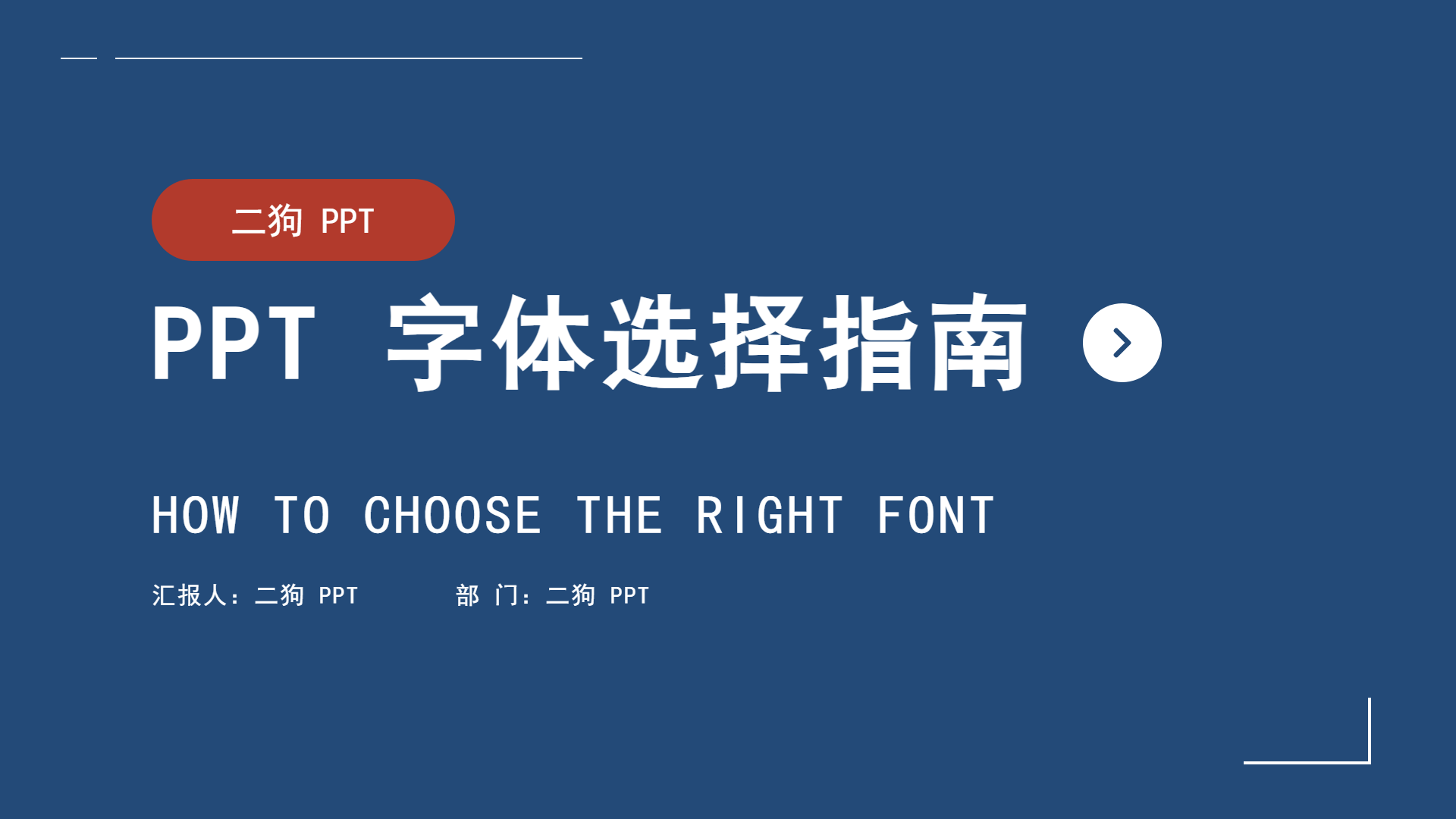
PPT 字体的选择原则
PPT字体的选取的重要准则,并非是好看,而是得清晰。
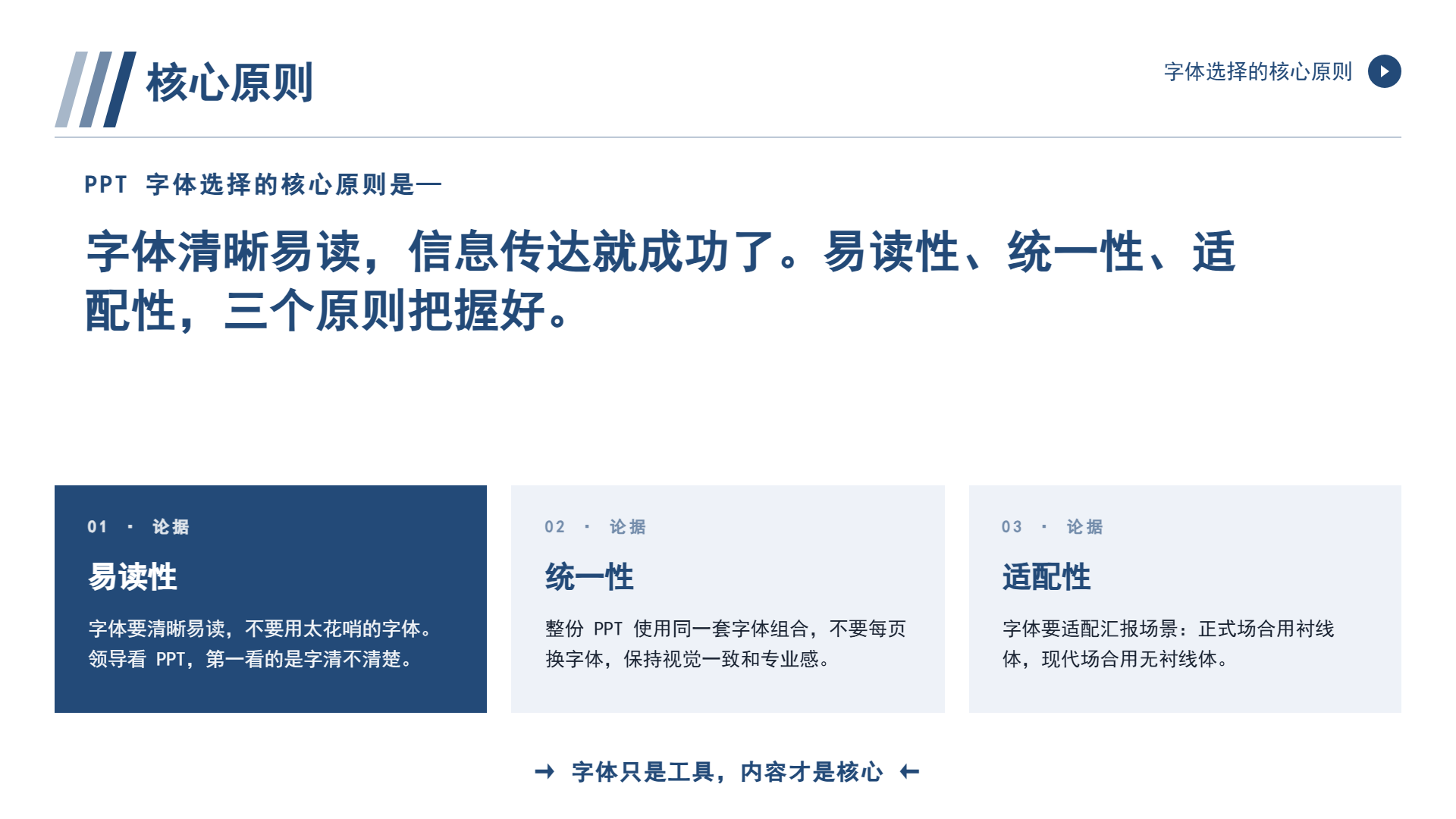
领导在查看PPT的时候,首要关注的是字是否清晰明了,而并非是字体好不好看。只要字体是清晰的,那么信息的传达就能够达成了。具体来说PPT字体的选择需要遵循三个方面的原则,分别是易读性、统一性以及适配性。
字体应当要清晰以便于阅读,不要采用过于花里胡哨的字体。整个 PPT 得使用同一种字体组合,不要每一页都更换字体。字体需要契合汇报的场景。在正式的场合运用衬线体,在现代的场合运用无衬线体。
PPT 字体的推荐组合
PPT字体予以推荐运用下面这些组合的状况。
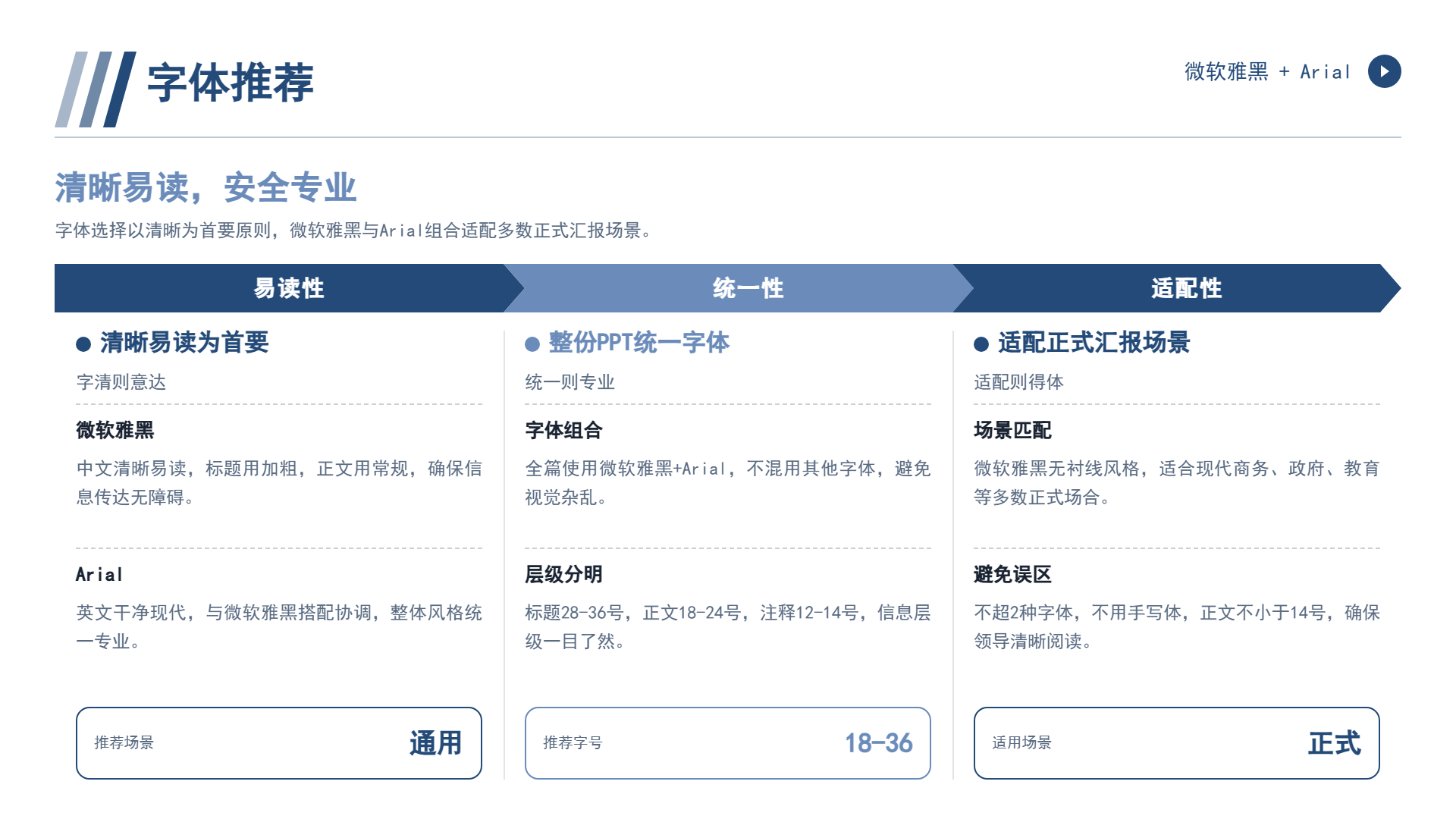
微软雅黑是一种较为安全的选择。微软雅黑看起来清晰还挺好读的,Arial,显得干净而且还挺现代的。标题使用加粗的微软雅黑,正文就用常规的微软雅黑,英文就用Arial。思源黑体是一种比较现代的选择。思源黑体的线条很清晰,Roboto简洁而且又现代。比较适合互联网和科技公司。宋体是最为正式的选择。宋体正式又稳重,Times New Roman经典而且又正式。适合国企还有学术汇报。
PPT 字体的字号建议
在 PowerPoint 字体的运用过程当中,字号的选取那可是一件至关重要的事情。
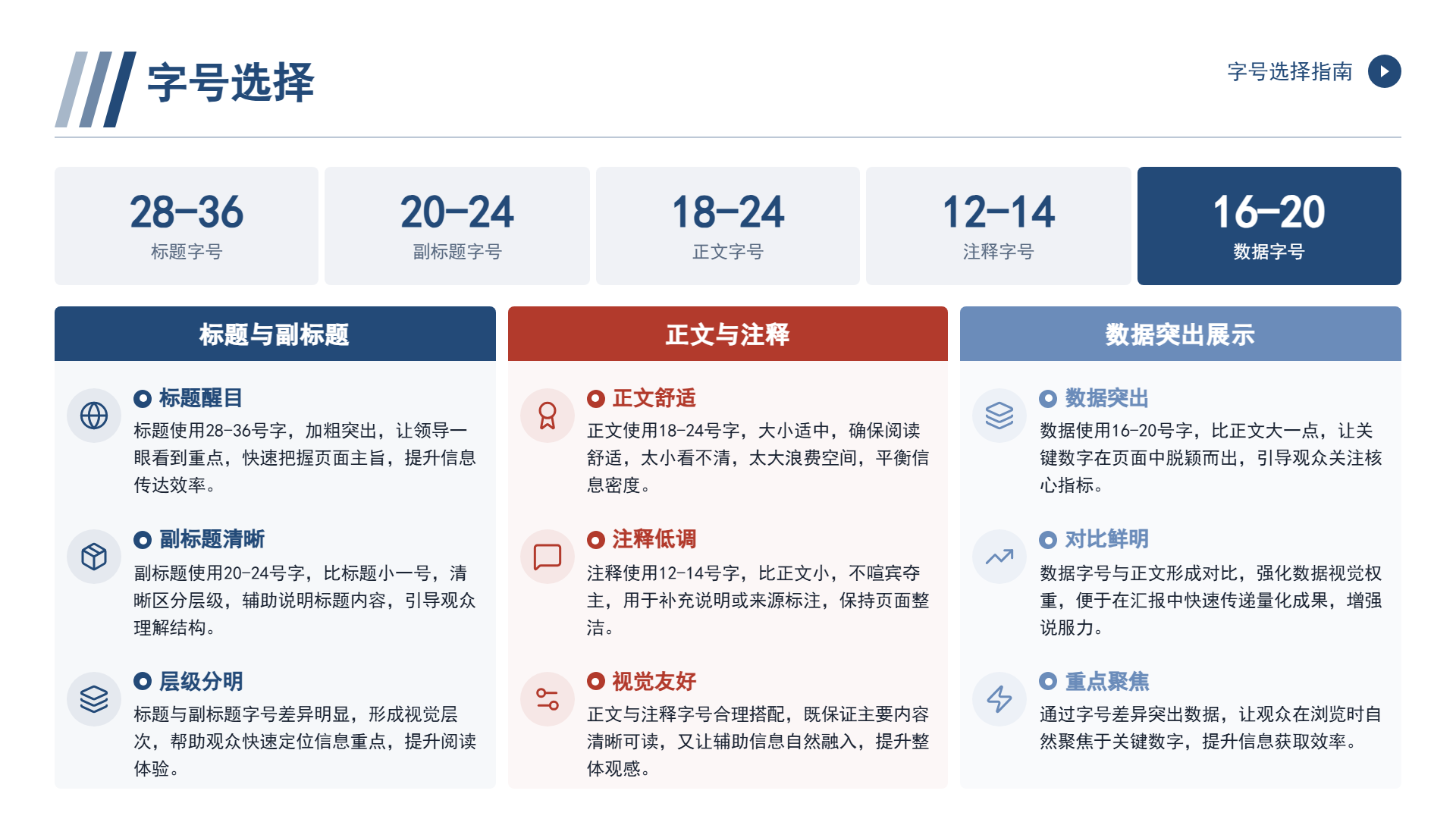
标题部分:运用28到36号字体,要让标题足够醒目,好让领导一眼就能看到。副标题部分:采用20到24号字体,要清晰明了,且比标题字体小一些。正文部分:使用18到24号字体,要让人看着感觉舒适,太小了会看不清,太大了又会造成空间的浪费。注释部分:运用12到14号字体,要小一点,不能去抢了主要内容的风头。数据部分:采用16到20号字体,要突出显示,比正文字体大那么一点。
PPT 字体的常见误区
PPT字体方面存在着好几个常见的错误性的认知,如果可以躲开这些错误之处,那么在字体的运用方面就已经成功了一大半。
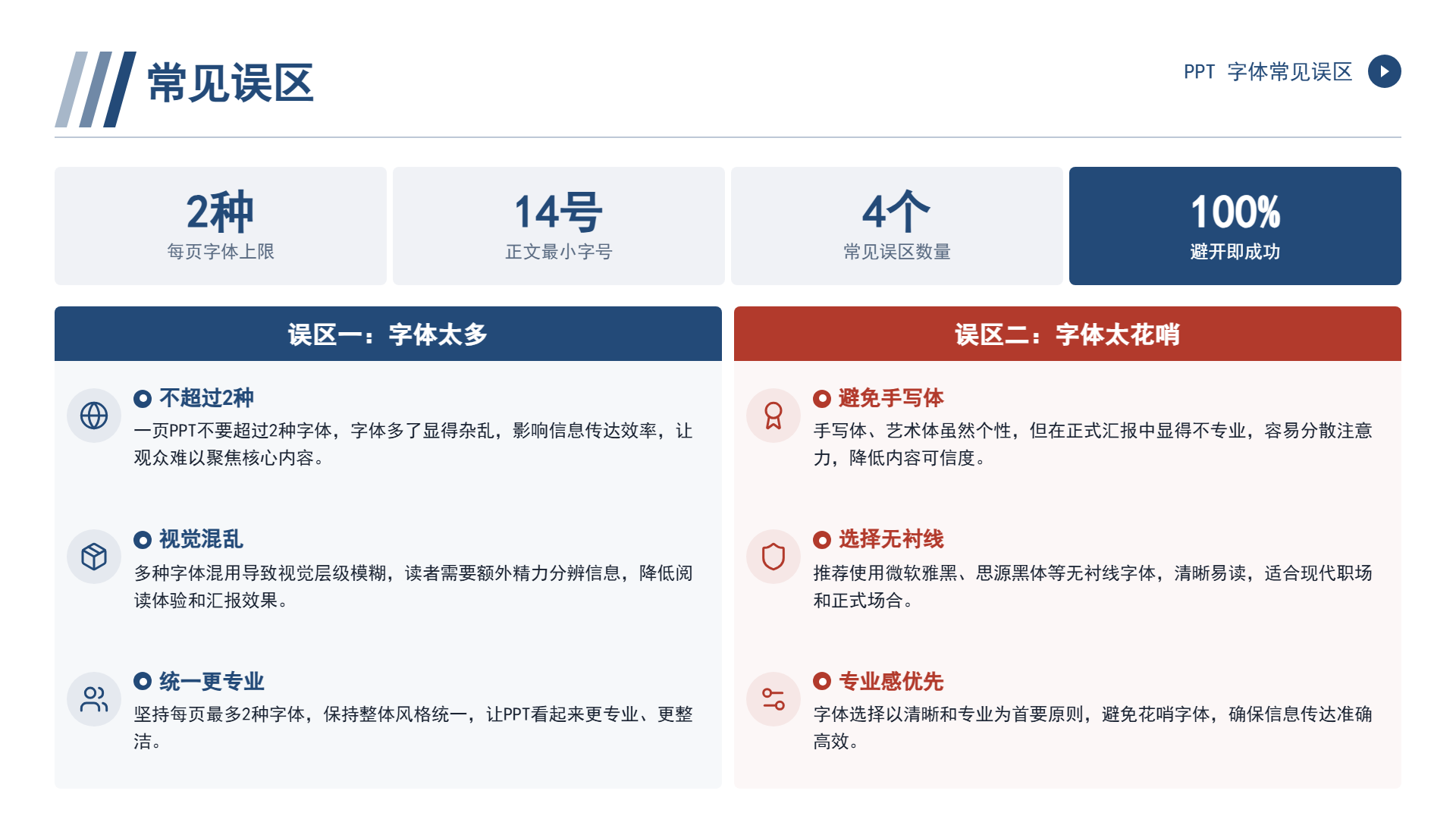
误区其一:字体不要过多。在一页的 PPT 当中所使用的字体不要超过两种。字体过多的话看起来会比较杂乱。误区其二:字体不要过于花哨。手写体、艺术体看起来不专业,不要使用。误区其三:字号不要过小。正文如果小于 14 号的话,领导就看不清楚。误区其四:字体需要统一。标题使用黑体,正文使用宋体,英文使用 Arial,不统一可不行啊。
PPT 字体的实用技巧
PPT字体存在着若干个具有实用性的小诀窍,倘若将这些小诀窍运用得较为出色,那么所呈现出来的效果便会极大幅度地得到提高。
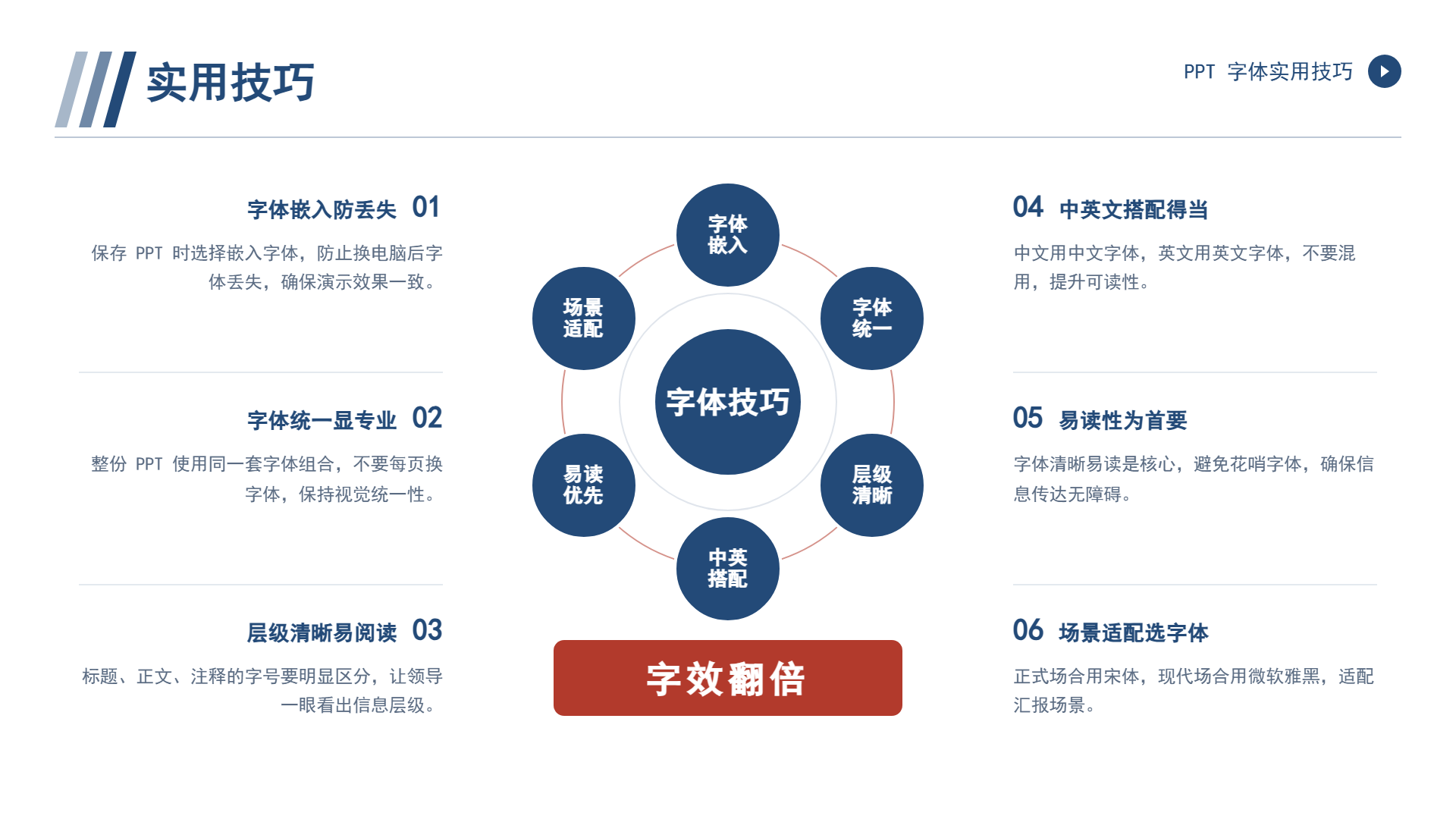
首先来讲讲字体嵌入这一方面的情况。在保存PPT的时候,需要去选择嵌入字体这样的操作,通过这样做能够防止换了电脑之后字体出现丢失的状况。接着是字体统一这一块。整份PPT得采用同一套字体组合,可不能出现每页都更换字体的情况。再然后是层级清晰这方面。标题、正文、注释的字号得要明显地区分开来,使得领导能够一下子就看出来信息的层级。最后是中英文搭配这一点。中文得使用中文字体,英文得使用英文字体,可不要混合着去使用。
常见问题
- PPT字体选择最重要的原则是什么?
最重要的原则是清晰,而非好看。字体必须易读,确保信息能够有效传达。
- 推荐哪些PPT字体组合?
微软雅黑加Arial适合通用场景;思源黑体加Roboto适合互联网科技公司;宋体加Times New Roman适合国企和学术汇报。
- PPT中标题和正文应该用多大字号?
标题建议28-36号,副标题20-24号,正文18-24号,注释12-14号,数据16-20号。
- PPT字体使用中有哪些常见误区?
常见误区包括:一页中使用超过两种字体、使用手写体或艺术体、正文小于14号、字体不统一。
- 如何避免换电脑后字体丢失?
在保存PPT时选择嵌入字体,可以防止字体丢失。同时整份PPT应使用同一套字体组合,并确保中英文分别使用对应字体。